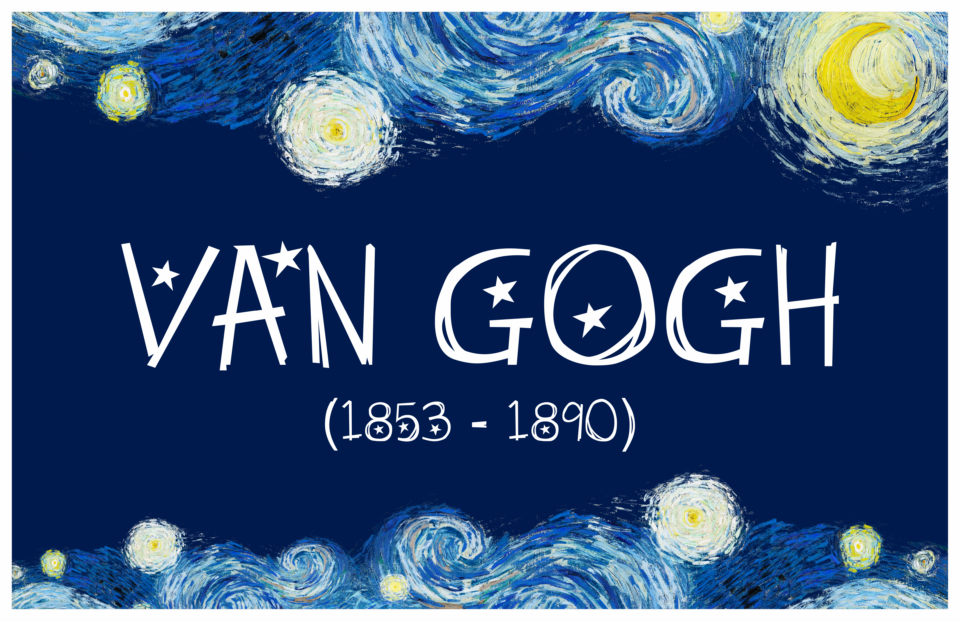
Font Việt Hóa DL Starry Night
Giới thiệu về Font Việt Hóa DL Starry Night
Nếu bạn đang tìm kiếm một Font Miễn Phí mang phong cách lãng mạn và bay bổng thì Font Việt Hóa DL Starry Night chính là sự lựa chọn hoàn hảo nhất. Đây là bộ phông chữ được thiết kế dựa trên cảm hứng từ bầu trời đêm đầy sao, với những đường nét thanh mảnh, uốn lượn mềm mại như những dải ngân hà. Việc sở hữu bản Việt hóa giúp các bạn học sinh và giáo viên dễ dàng ứng dụng vào các bài thuyết trình, thiết kế thiệp chúc mừng hay làm tiêu đề cho các báo cáo học thuật thêm phần sinh động.
Ưu điểm nổi bật của Font Việt Hóa DL Starry Night trong thiết kế
Nét vẽ thủ công tinh tế
Điểm đặc biệt của Font Việt Hóa DL Starry Night nằm ở sự kết hợp hài hòa giữa phong cách viết tay calligraphy và tính hiện đại. Các ký tự được chăm chút tỉ mỉ, tạo cảm giác gần gũi nhưng không kém phần sang trọng. Đối với các dự án thiết kế đòi hỏi tính cá nhân hóa cao, bộ font này giúp truyền tải cảm xúc một cách trọn vẹn, biến những dòng văn bản khô khan trở nên có hồn và thu hút người xem ngay từ cái nhìn đầu tiên.
Khả năng tương thích và hiển thị
Kết luận về bộ font nghệ thuật này